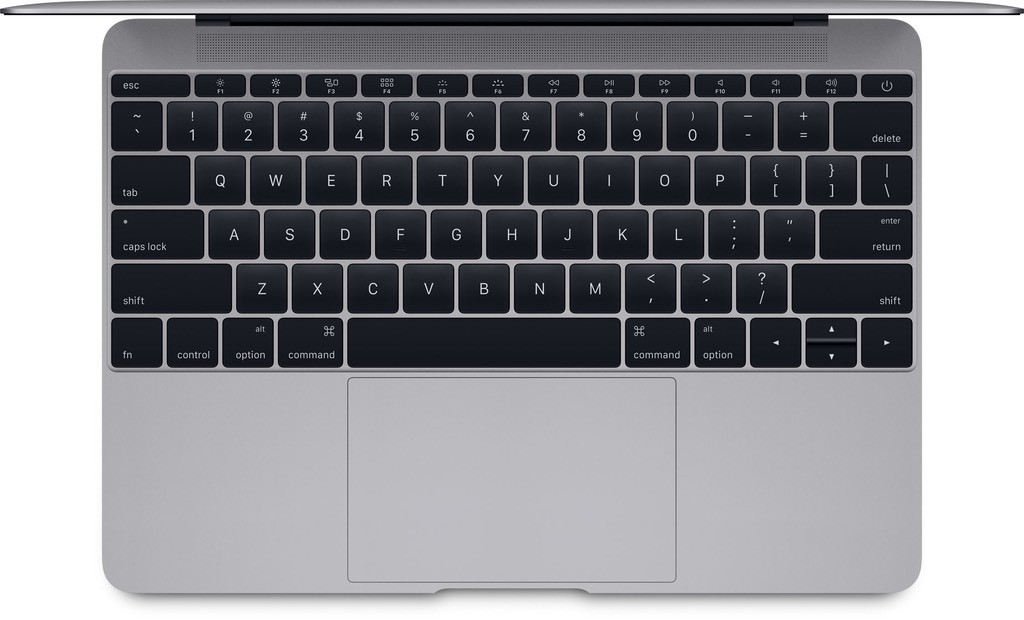
Nuovo MacBook, Apple ha cambiato il font dei caratteri sulla tastiera
Piccola novità per la tastiera dei nuovi MacBook: i caratteri serigrafati sui tasti usano un nuovo font; il vecchio “VAG Rounded” usato sui portatili Apple sin dal 1999 lascia il posto a “San Francisco”, lo stesso carattere usato dalla multinazionale della Mela per Apple Watch. Creato per le necessità del gruppo Volkswagen alla fine degli anni ’70, VAG Rounded è una sorta di variante arrotondata di Futura, ideato per testi tecnici, manuali d’istruzioni e pubblicità; abbandonato dal costruttore d’auto tedesco nel 1992, ha conosciuto una nuova vita con l’avvento dei servizi per il web 2.0. Tra i logo noti che usano ancora il vecchio font Vag Rounded, quello della Rede Globo, rete televisiva brasiliana.
Per quanto riguarda il font “San Francisco”, Apple spiega che è stato specificatamente pensato per essere molto leggibile anche quando è usato in abbinamento a display di piccole dimensioni. Il cambio del font impiegato per la tastiera del nuovo MacBook introdotto durante il keynote del 9 marzo dedicato soprattutto ad Apple Watch, non è passato inosservato agli appassionati di grafica e Mac. L’attenzione del pubblico mondiale si è naturalmente concentrata sul nuovo design incredibilmente sottile e leggero e sulle novità hardware di questo notebook futuristico e minimalista. In realtà sia la tastiera che il nuovo touchpad hanno suscitato commenti contrastanti tra giornalisti e media che per primi hanno potuto toccare con mano il nuovo MacBook, subito dopo il keynote. Secondo alcuni occorre un po’ di pratica per familiarizzare con entrambi, secondo altri invece i nuovi touchpad e tastiera risultano subito immediati da usare.